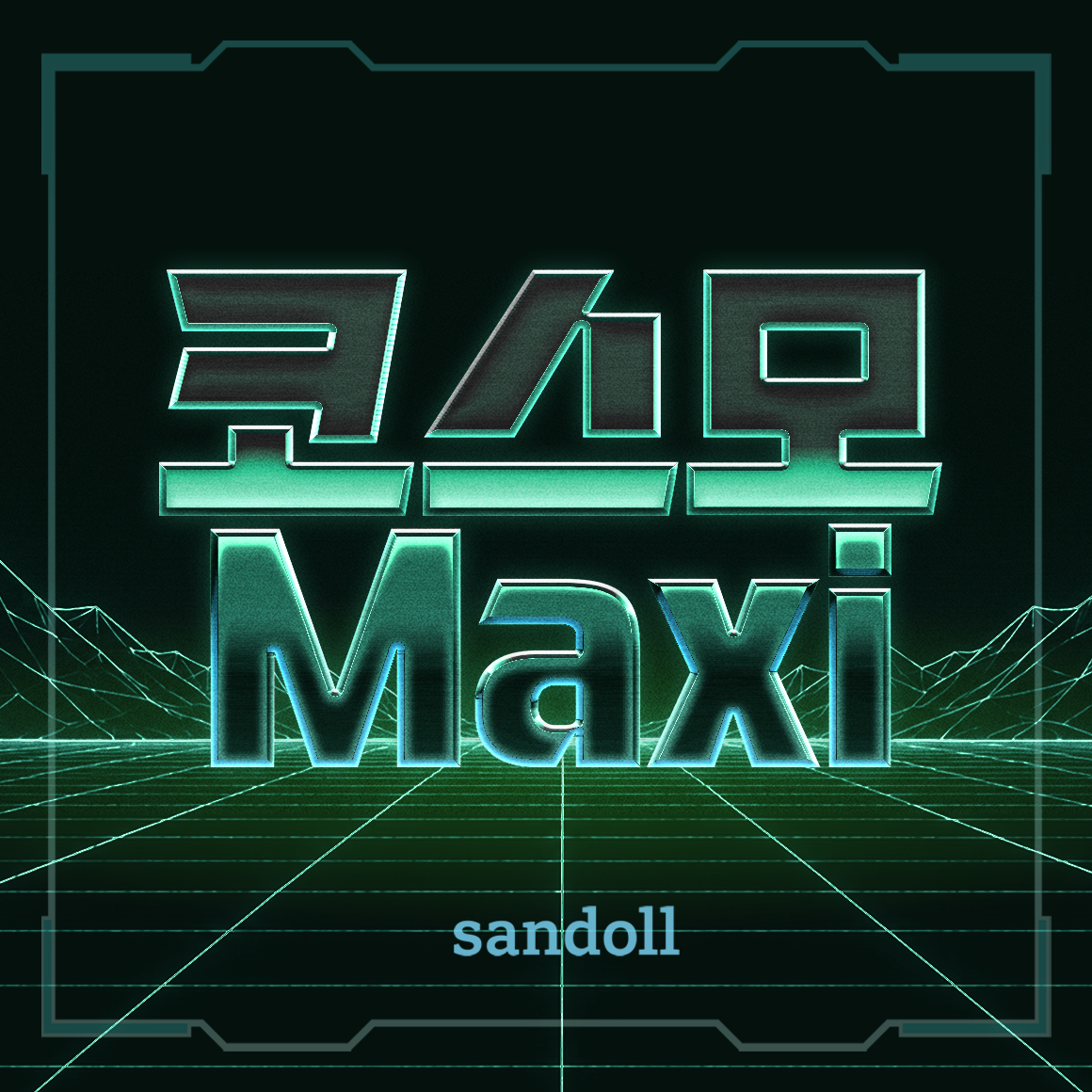
SD 코스모 Maxi
「SD 코스모 Maxi」는 레트로 퓨처리즘을 주제로 디자인된 제목용 폰트 「SD 코스모」를 기반으로, 더욱 네모꼴에 가깝고 꽉 찬 비례로 확장한 버전입니다. 직선적이고 대각선으로 커팅된 획이 만들어내는 기계적이고 사이버틱한 인상은 그대로 유지하면서, 글자 내부의 공간을 더욱 밀도 있게 채워 강한 존재감과 시각적 임팩트를 더했습니다. 특히 삼각형 형태의 백색공간과 네모꼴에 가까워진 구조가 만들어내는 리듬감은 미래적이고 구조적인 분위기를 한층 강조합니다.